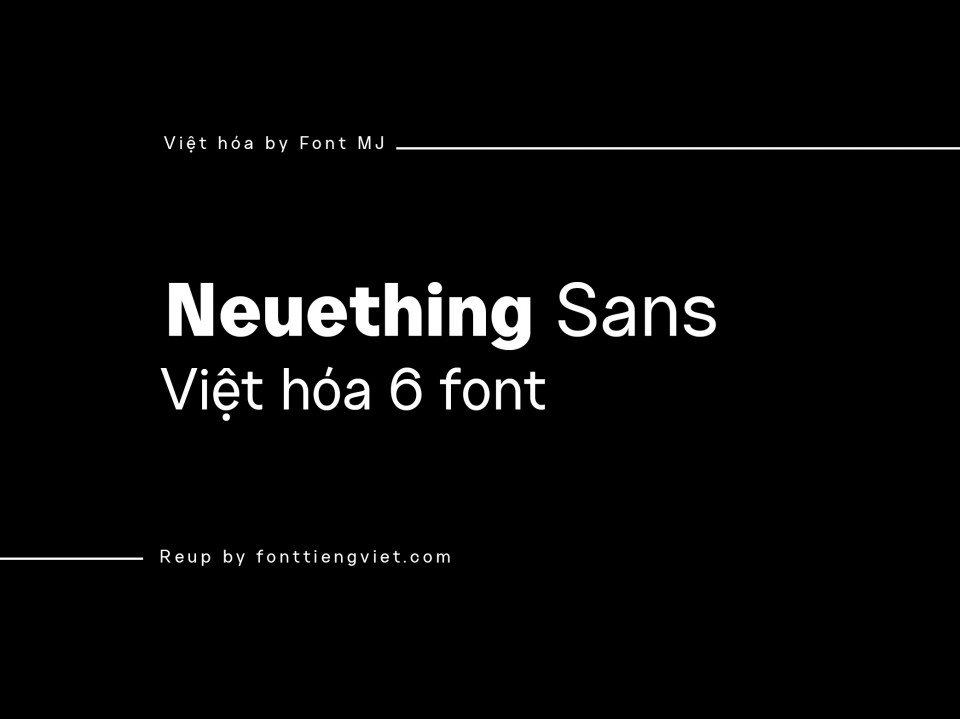
Giới thiệu về bộ Font việt hoá MJ Neuething Sans (6 font)
Trong thế giới thiết kế đồ họa hiện đại, việc tìm kiếm một bộ Font Chữ đáp ứng cả tính thẩm mỹ lẫn khả năng đọc hiểu là ưu tiên hàng đầu. Font việt hoá MJ Neuething Sans (6 font) chính là giải pháp hoàn hảo dành cho những ai yêu thích phong cách tối giản nhưng không kém phần tinh tế. Bộ font này được lấy cảm hứng từ các kiểu chữ không chân (sans-serif) đương đại, mang lại cảm giác sạch sẽ, gọn gàng và vô cùng chuyên nghiệp. Với cấu trúc hình học chuẩn xác, đây là lựa chọn lý tưởng cho các bạn học sinh, sinh viên và giáo viên khi trình bày giáo án điện tử hoặc làm bài thuyết trình ấn tượng.
Đặc điểm nổi bật của MJ Neuething Sans
Đa dạng phong cách với 6 biến thể
Bộ Font việt hoá MJ Neuething Sans (6 font) bao gồm sáu định dạng khác nhau từ Light, Regular đến Bold. Sự đa dạng này cho phép người dùng linh hoạt trong việc phân cấp nội dung, giúp các tiêu đề trở nên nổi bật trong khi phần thân văn bản vẫn giữ được sự thanh thoát, dễ nhìn. Đặc biệt, các ký tự tiếng Việt đã được tinh chỉnh tỉ mỉ, đảm bảo không bị lỗi dấu hay sai lệch khoảng cách khi gõ văn bản phức tạp.
Ứng dụng rộng rãi trong học đường và đời sống
Nhờ vẻ ngoài hiện đại, bộ font này cực kỳ phù hợp để thiết kế bìa sách, poster sự kiện trường học hoặc các infographic học tập. Tính ứng dụng cao và giao diện thân thiện giúp MJ Neuething Sans trở thành công cụ hỗ trợ đắc lực cho việc sáng tạo nội dung số tại Việt Nam.